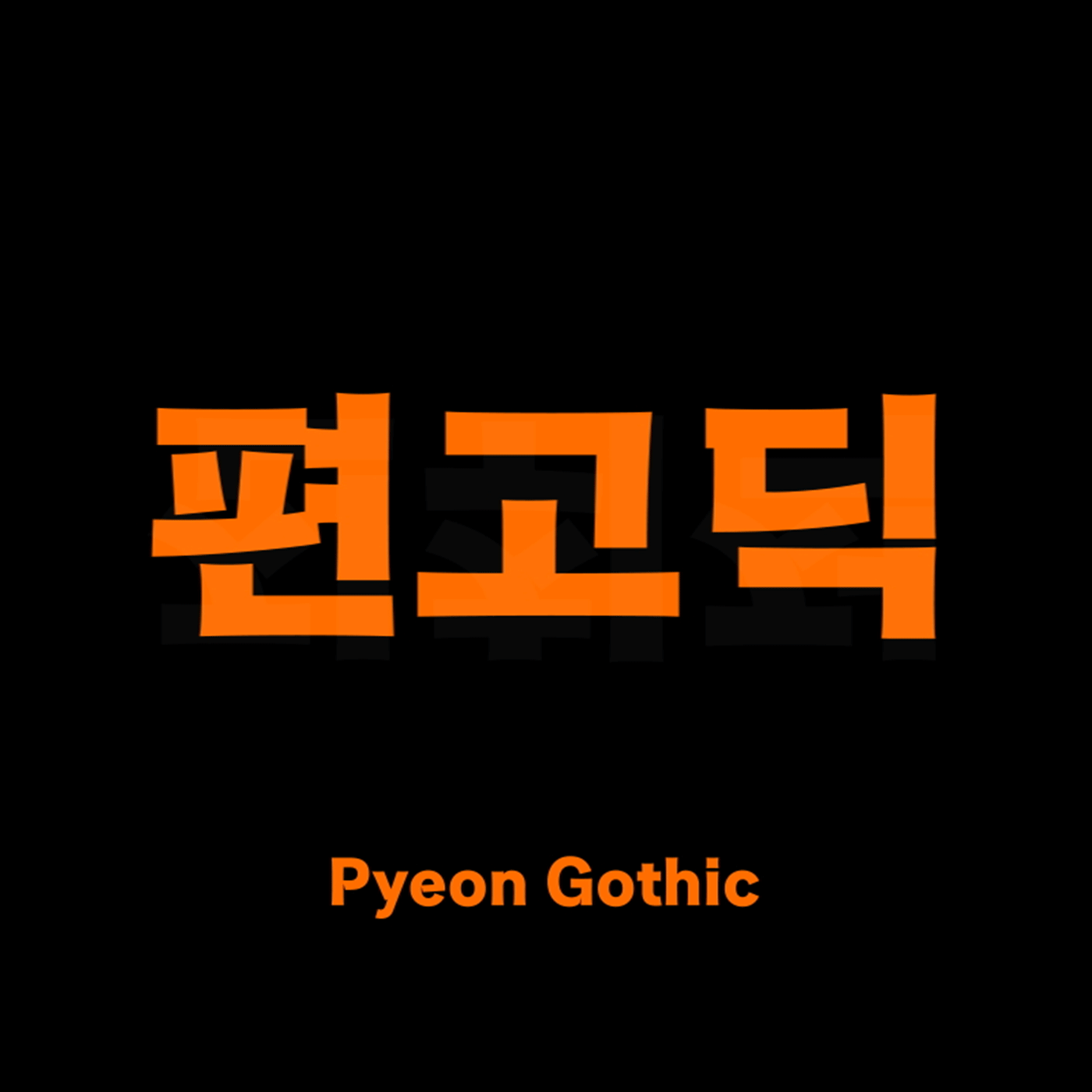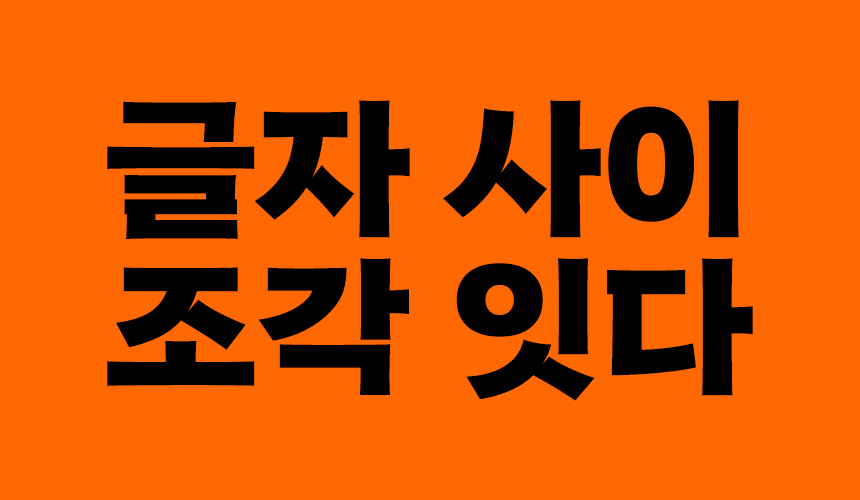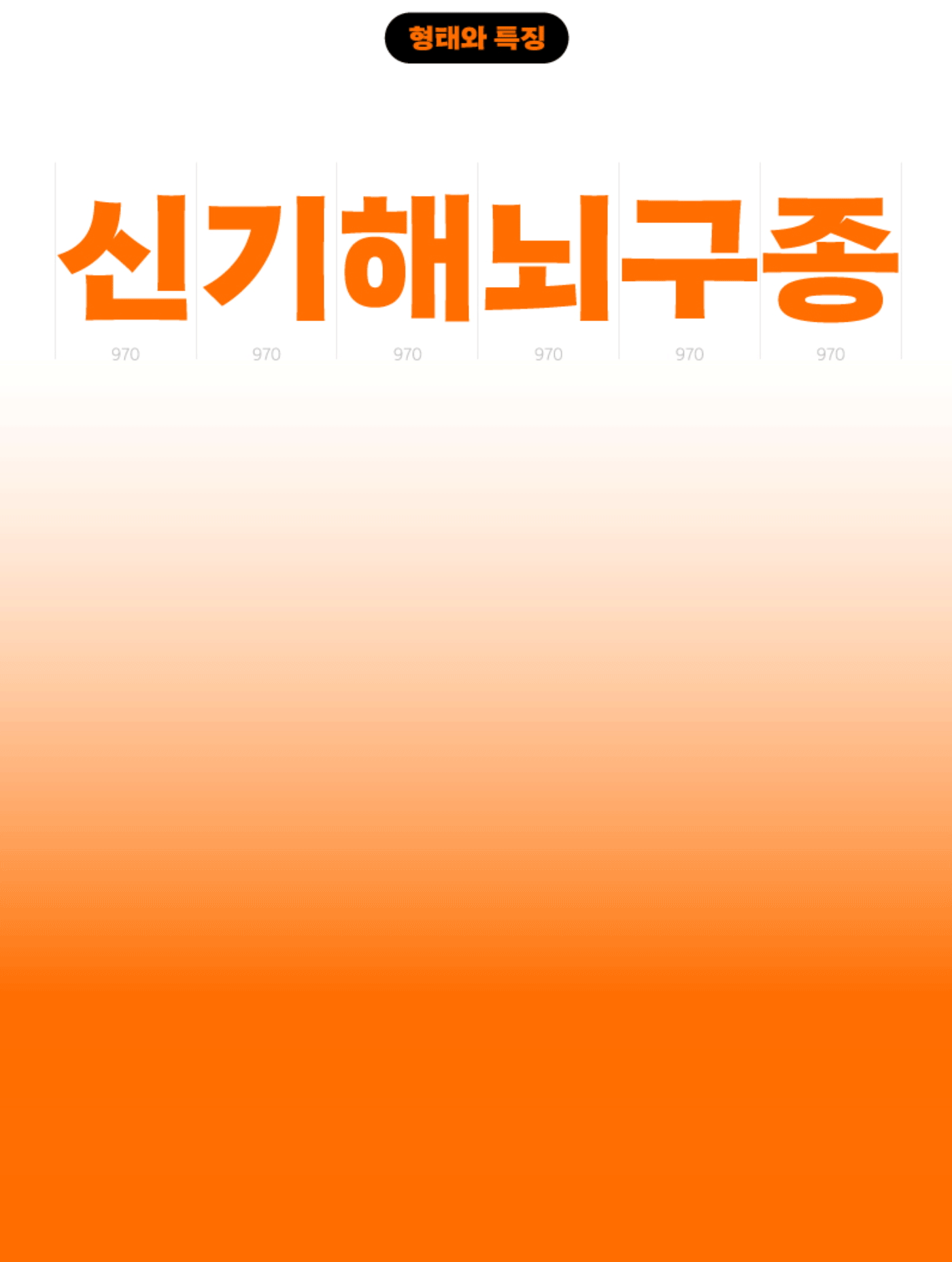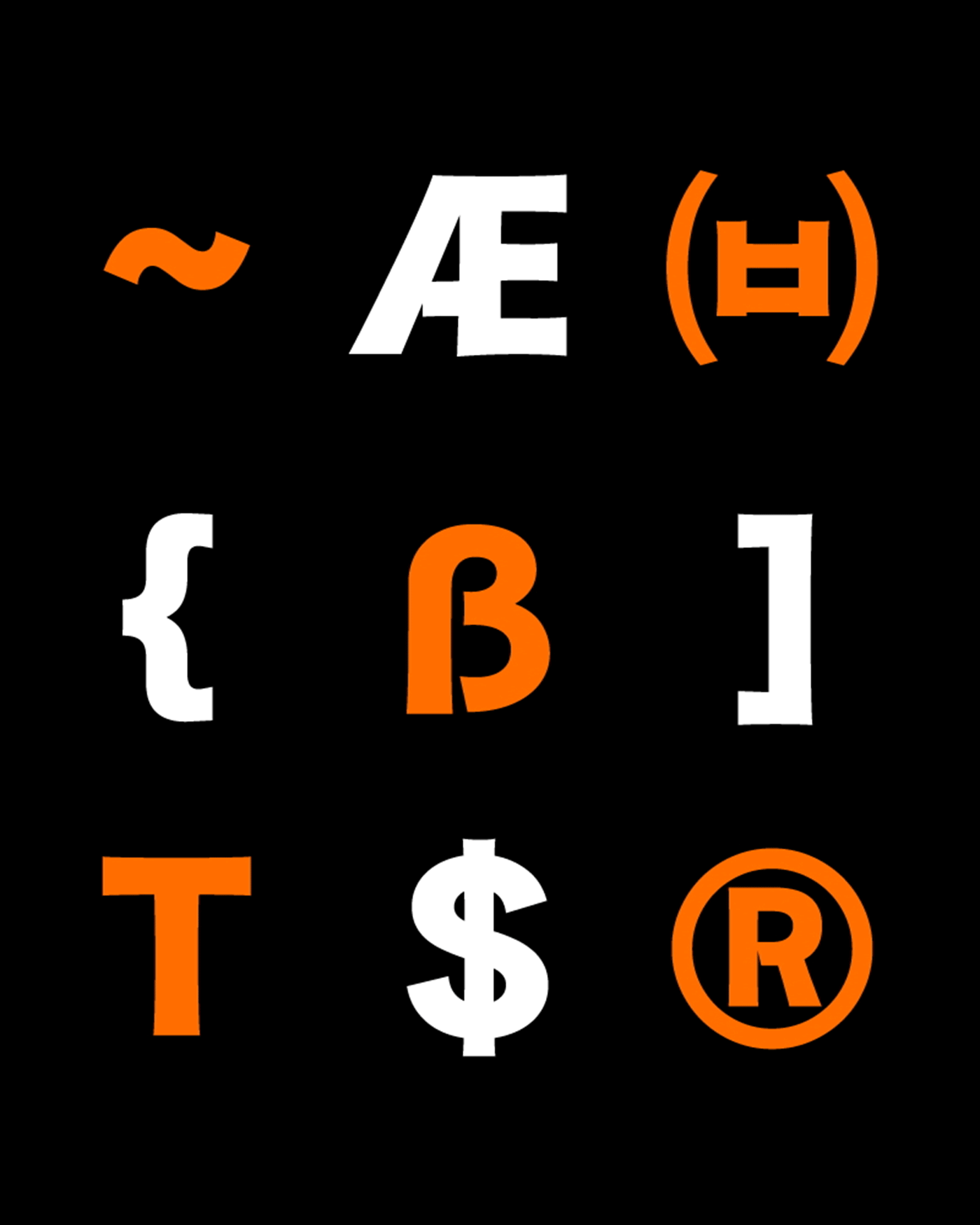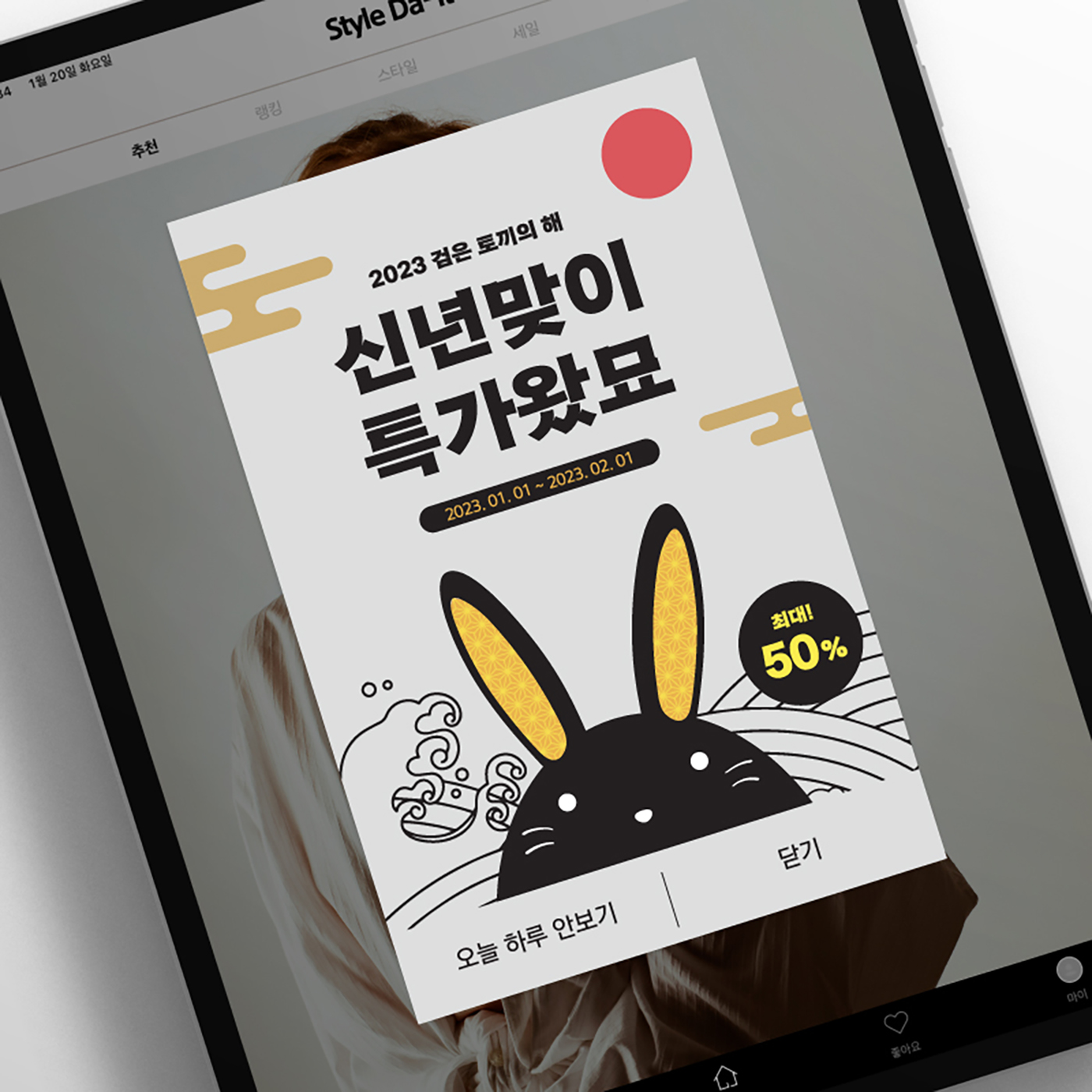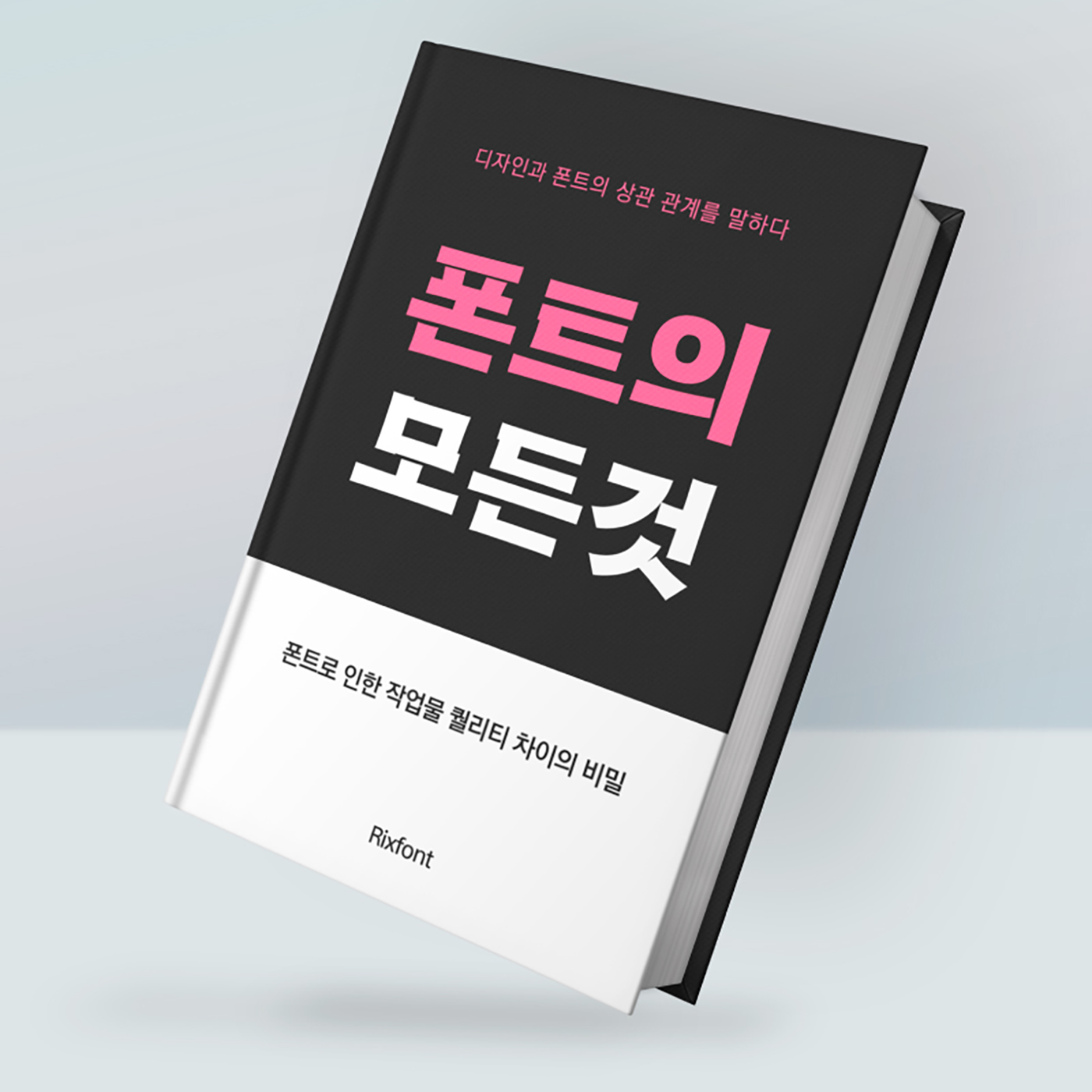
안녕하세요. 2023년 새해가 밝았는데요! 오늘은 즐거운 시작 1월, 올해의 첫 신규 폰트 「Rix편고딕」를 소개합니다. Rix편고딕은 전체적으로 텐션감이 있는 형태로 활기를 띠며 단단한 인상을 가진 헤드라인 글꼴입니다. 폰트를 기획하고 디자인한 박지영 디자이너와의 인터뷰를 통해 더 자세히 알아볼게요 :)
'Rix편고딕'은 어떻게 기획했고 또 서체명은 어떻게 지어졌는지 궁금해요.
편고딕은 필력이 느껴지는 산세리프 서체를 만들어보고 싶어서 기획하게 된 서체입니다. 1년 전쯤 인턴 시절에 했던 기획이고, 디렉팅 해주신 박용락 프로님과 주변 동료들의 피드백, 그리고 점점 바뀌는 저의 미감에 의해 중간중간 많은 수정을 거쳤습니다. 편고딕이란 이름은 고딕 앞에 조각 편(片)자를 써서 붙이게 된 이름입니다. 자소 형태의 틈이 조각 난 것 같아 그렇게 지었습니다. 사실 이름을 정하는 게 생각보다 힘들었어요. 편이란 글자는 보통 안 좋은 단어에 붙기 마련이지만, ‘편고딕’이란 이름 자체가 중립적인 느낌이라 저는 오히려 좋다고 생각했습니다. 힘 있는 말이나 중립적인 비문학 제목에 사용하면 좋겠다고 생각했으니까요.
디자인에 영감을 얻은 것이라면?
영화 포스터의 타이틀이나 광고 배너의 자소 형태를 보고 처음 기획하게 되었습니다. 쓰여지는 각도에 따라 자연스럽게 틈이 생기는 모습에 재미를 느꼈어요.
사람들이 많이 찾는 매력적인 폰트가 되기 위한 ‘한 가지’를 꼽자면?
서체에 어떤 표현을 입혔든 간에 고르고 일정함에서 오는 단정한 멋이 느껴질 때가 있습니다. 그것이 폰트를 만들 때 가장 기본적인 것이겠지만, 원래 기본이 가장 어려운 법이잖아요. 그리고 그런 면에서 많이 부족한 저를 느끼고요. 점점 더 나아지겠지 하고 있습니다!
조각과 조각을 잇다
먼저 두꺼운 획과 단단한 골격이 눈에 띄는 Rix편고딕 서체는 자소 사이사이에 있는 틈이 조각이 난 듯 이어져 있습니다. 이 조각(크랙)들이 어우러져 기본적인 고딕체와는 다른 분위기를 줍니다.
970의 여유로운 고정 자폭이 한층 담담하고 여유로운 멋이 느껴지도록 설계했습니다. 전체적으로 직선적이지만 손글씨의 맛을 살린 자연스러운 곡선들이 어우러져 조화롭고 텐션감이 있는 특징이 있습니다.
단단하고 활기찬 인상
거친 필력과 날카로운 크랙이 있어 아무래도 강한 어조에 잘 어울리는데요. 고딕의 단단한 느낌, 손글씨의 성격이 느껴지는 활기찬 이미지가 동시에 느껴집니다.
숫자, 영문, 여러 특수 기호들도 동일한 스타일이 적용되고 특징적인 크랙 요소를 배치해 통일감 있는 디자인이 가능합니다.
이렇게 활용해 보세요🪄
제목용으로 사용할 경우 주목도가 높아 웹 배너나 북 커버, 유튜브 썸네일 등 타이틀에 활용하기 좋습니다. 적당히 굵은 두께를 갖고 있기 때문에 크게 들어가는 자막이나 강조하는 문구에도 사용하면 좋을 것 같습니다.
이렇게 한글과 영문이 함께 보여져도 이질감이 없고 조화롭기 때문에 다방면으로의 활용이 기대되는데요, 크랙 디테일을 잘 활용하여 기본에 충실하지만 특징도 살아있는 매력적인 글꼴로 사용할 수 있습니다.